Font chữ ký là những font chữ viết tay được các nhà thiết kế sử dụng để chèn lên tác phẩm đồ họa của mình. Font chữ ký thường là những kiểu chữ thanh mảnh, mềm mại, mang sắc thái cổ điển và thanh lịch…
Một trong những cách trình bày chữ ký được các nhà thiết kế ưa chuộng chính là sử dụng một bức ảnh chữ ký có nền đèn và nổi bật với dòng chữ trắng.
Font chữ ký việt hóa Scripture
Scripture: font chữ kết hợp “Script” và “Signature” xứng đáng được xếp đứng đầu danh sách này. Scripture với những nét mảnh, thanh thoát và dường như được sinh ra để làm chữ ký vậy.
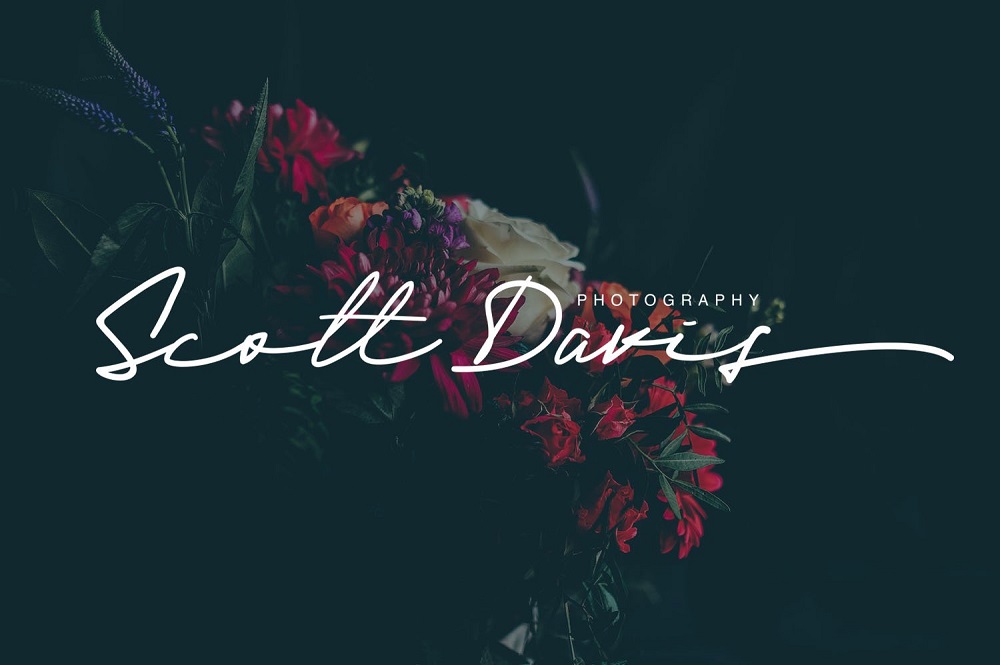
Font chữ ký việt hóa Like Father Like Son
Tương tự với Scripture, font Like Father Like Son cũng nổi bật với những nét mảnh tuy nhiên phóng khoáng hơn hẳn, mang đến cho thiết kế của chúng ta một cảm xúc “thủ công” đích thực.
Font này phù hợp với chữ ký, văn phòng phẩm, logo, tạp chí, áo quần, thiết kế bao bì, v.v..
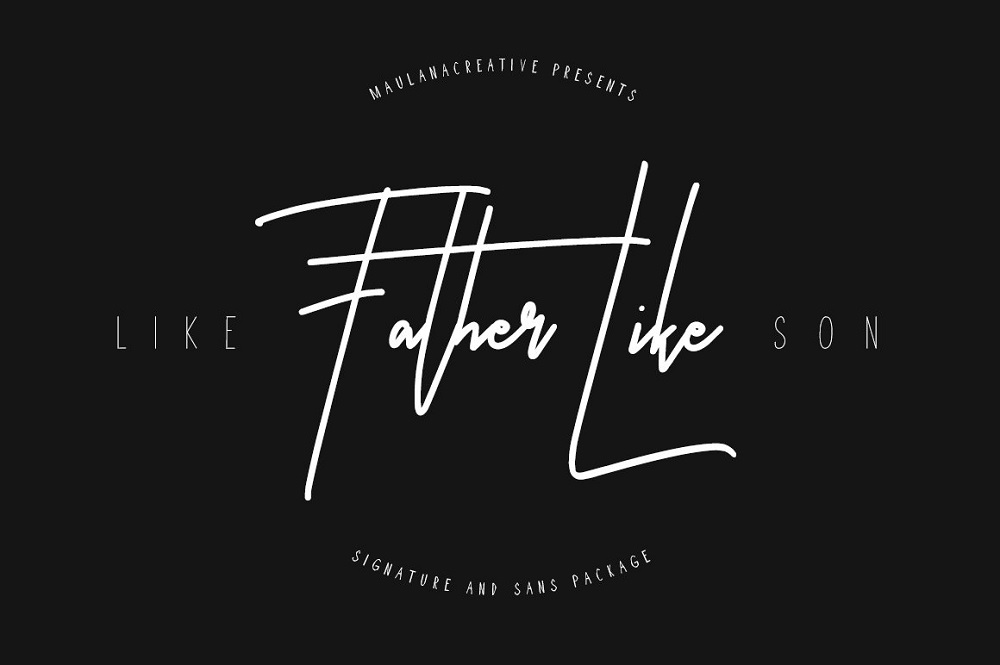
Font chữ ký việt hóa Astronout
SVN Astronout cũng là một lựa chọn thú vị trong dòng font chữ ký. Font thích hợp khi sử dụng trong typography, bìa sách, quần áo, bao bì… SVN Astronout được Việt hóa bởi STYLEno.1 Fonts
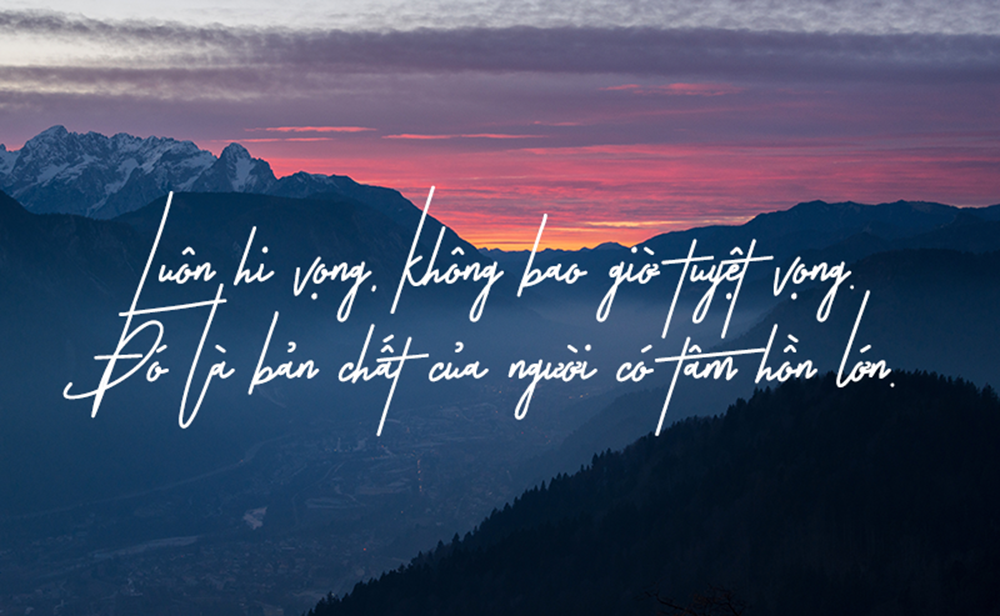
Font chữ ký việt hóa Iciel Romantically
Iciel Romantically là font chữ mang phong cách tự nhiên, nhẹ nhàng nhưng toát lên vẻ đẹp sang trọng, lịch lãm. Iciel Romantically được người dùng biết đến là kiểu font chữ viết tay tốc ký, được sử dụng trong nhiều phong cách, lĩnh vực khác nhau.
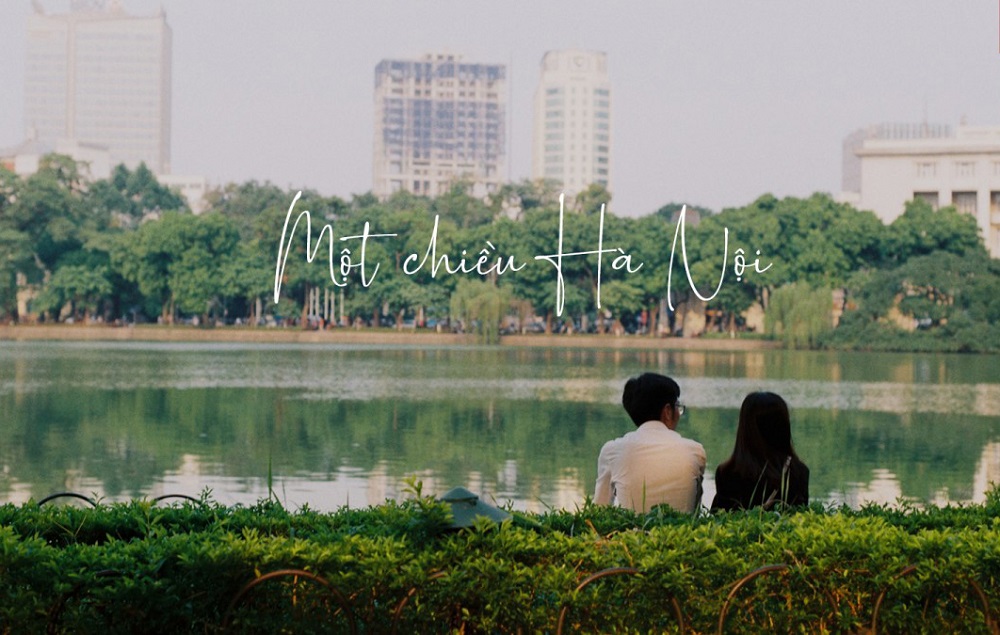
Font chữ ký việt hóa Rossela
Nếu bạn hướng tới phong cách tự nhiên, đơn giản, thì không nên bỏ qua font chữ Rossela để tạo chữ ký đánh dấu vào các tác phẩm của mình. Rossela mang đậm chất nét chữ viết tay đẹp.
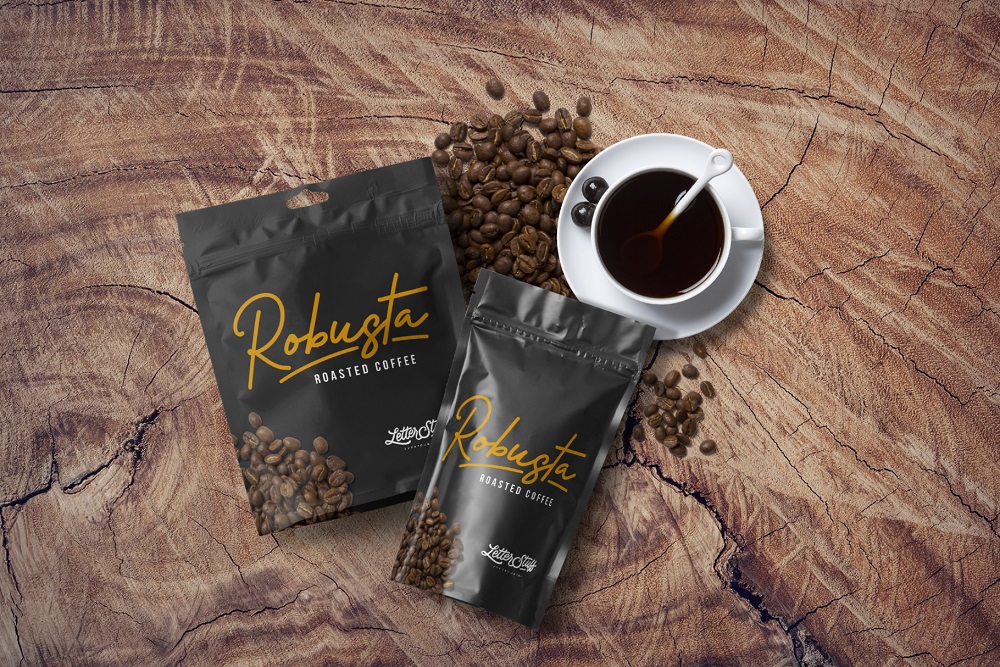
Font chữ ký việt hóa Just Awesome
Font chữ Just Awesome sẽ giúp bạn sở hữu những chữ ký mềm mại, đậm chất nghệ thuật. Ngoài ra, bạn có thể sử dụng Just Awesome để làm tiêu đề, chèn text vào ảnh, poster...
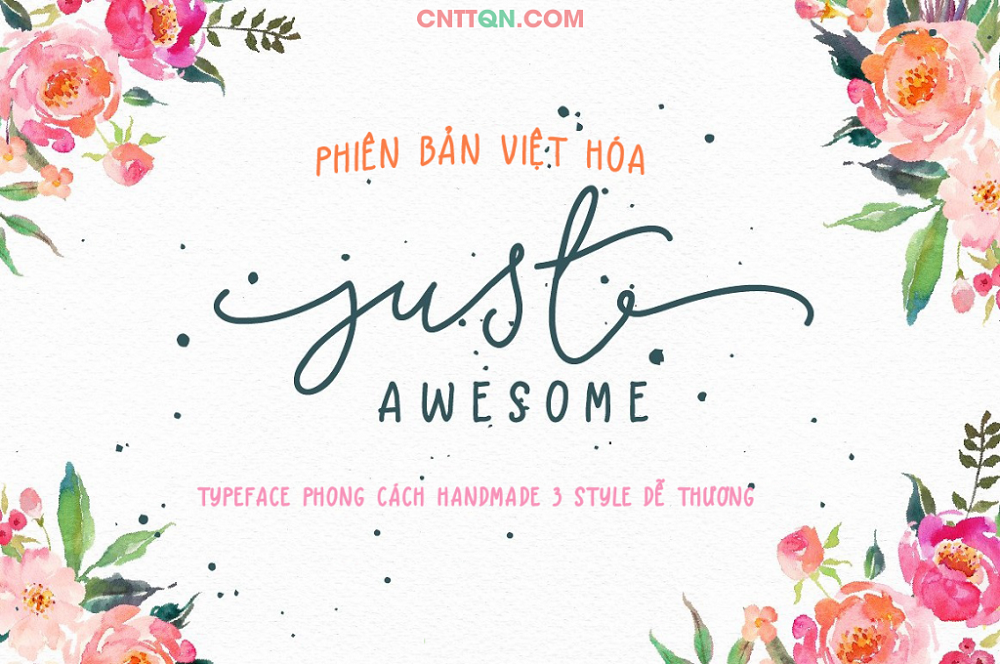
Font chữ ký việt hóa Imogen Agnes
Font chữ Imogen Agnes với phong cách đơn giản, nét chữ tinh tế là một trong những lý do được người dùng sử dụng nhiều làm font chữ ký.
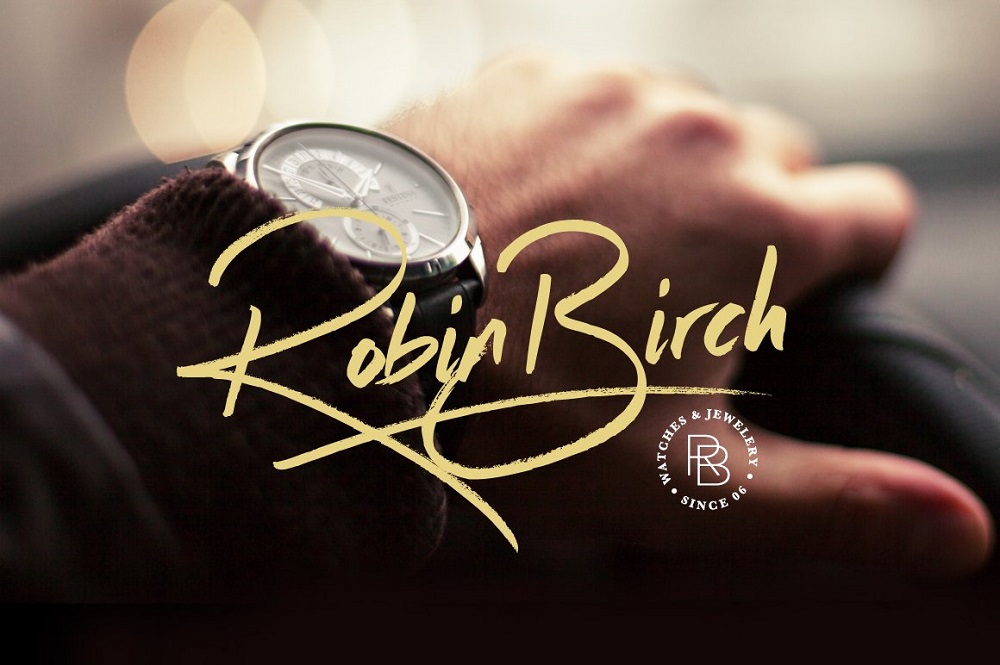
Font chữ ký việt hóa Bellwethers
Bellwethers mô phỏng lại chữ viết tay một cách tự nhiên và chân thật với những nét chữ thanh mảnh, thanh thoát. Đây là một font chữ mang đậm tính cá nhân, thu hút người xem.
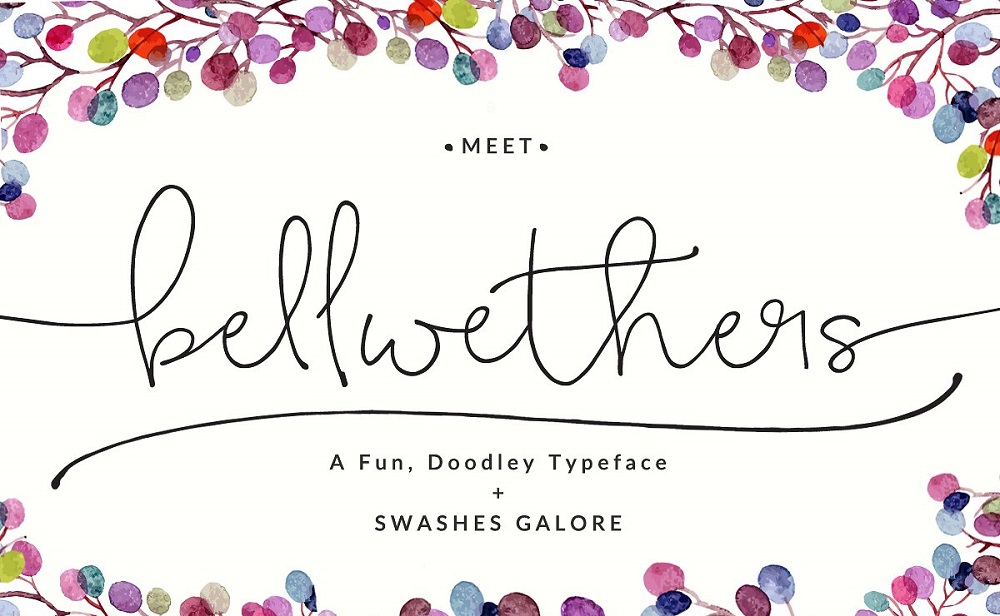
Font chữ ký việt hóa LovepenTypeface
Cũng như Bellwethers, Lovepen Typeface cũng mô phỏng chữ viết tay nhẹ nhàng, thanh thoát với nét bút mượt mà. Nếu bạn thích kiểu chữ ký đơn giản, tự nhiên thì nên thử qua font chữ này nhé.
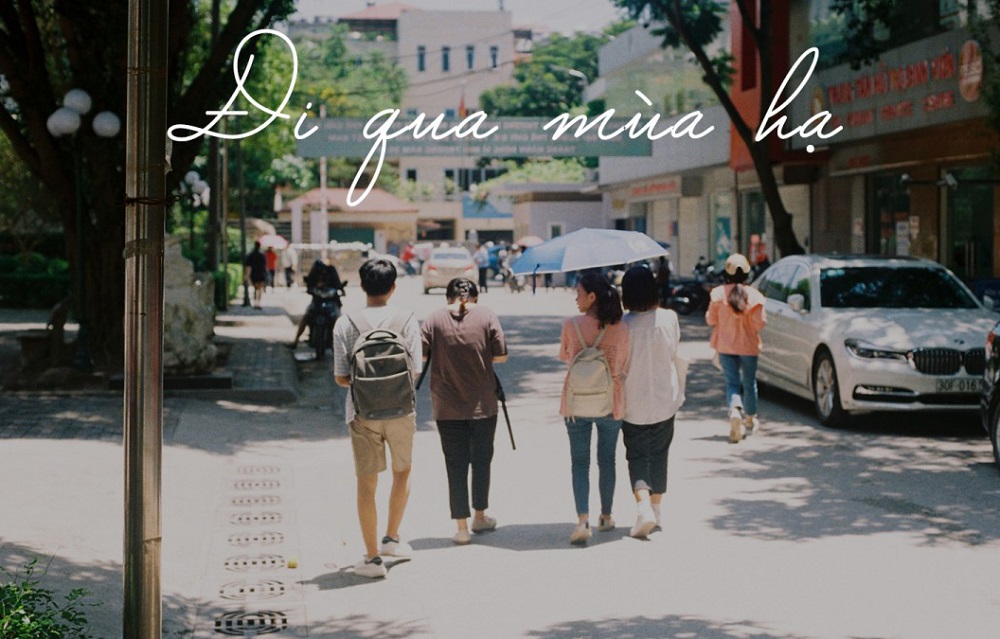
Font chữ ký việt hóa Hipsteria
Hipsteria mang đậm chất chữ viết tay với các nét chữ bay lượn mềm mại. Kiểu chữ mềm mại nhưng thu hút người xem, phù hợp với những bạn thích phong cách vintage, mộc mạc.